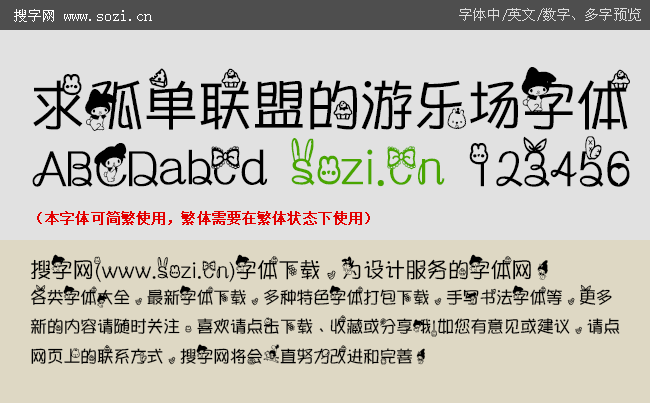
求孤單聯(lián)盟的游樂場(chǎng)字體
搜字網(wǎng)給大家提供一款很卡通的手機(jī)中文字體下載。修改者給這款字體叫求孤單聯(lián)盟的游樂場(chǎng)字體,這款手機(jī)中文字體以POP字體為原形,在筆畫間嵌入了大量非常可愛的卡通圖形,該中文字體趣味性強(qiáng),又保持了文字的識(shí)別度,非常適合喜歡卡通的朋友在手機(jī)上安裝使用。